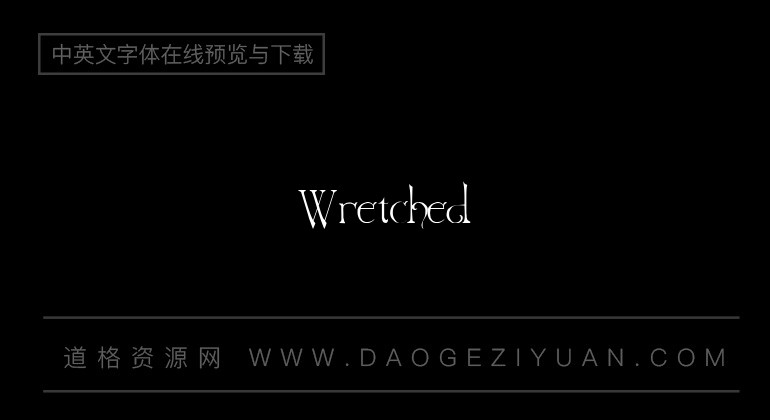
Wretched 字体是一种印刷风格的字体。它的设计灵感来源于手工刻字,其特点是线条粗细不一,形状不规则,给人一种粗犷、野性的感觉。 该字体的字形较为简单,字母间距较小,适合用于标题、海报、宣传单等具有强烈视觉冲击力的设计中。它的颜色较深,不适合用于大篇幅的排版,但可以用于强调特定词语或段落。 Wretched 字体适用于印刷品、数字设计、艺术装饰和标志设计等领域。它的独特风格可以帮助设计师在视觉上吸引观众的注意力,突出设计的主题和氛围。内容介绍
Wretched是一款非常不错的手写艺术字体,具有很好的视觉感,适合于文化类的宣传设计、商业类品牌的广告和产品包装设计以及个性化文字排版等较多场景。